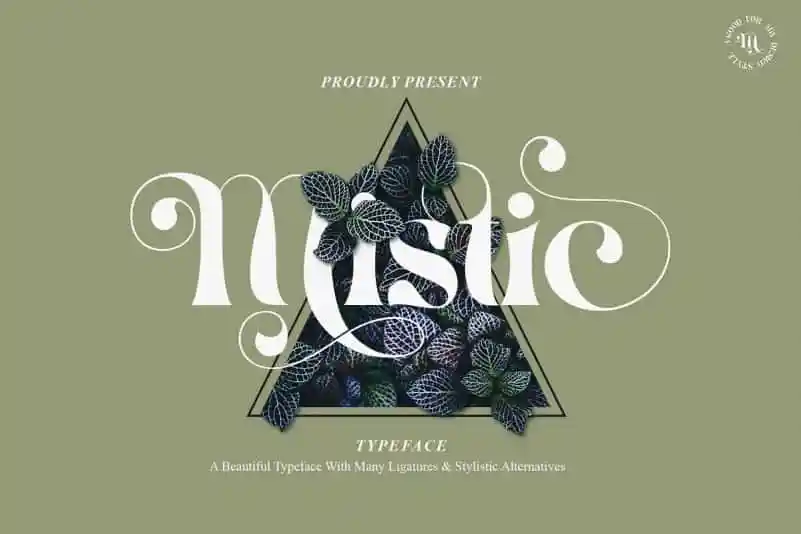
A Mistic Serif Font é uma escolha perfeita para quem busca um estilo elegante e sofisticado que destaca suas criações. Desenvolvida pelo alit design, esta fonte serif se destacou graças ao seu uso recorrente no setor dos casamentos. O conceito desta fonte é marcado por uma elegância brilhante, repleta de alternativas com letras curvadas, que adicionam um toque romântico às criações. Perfeita para trabalhos relacionados a temáticas como casamentos, cartões de aniversário, citações românticas e muitos outros temas relevantes. Englobando essas características, a Mistic Serif Font surge como uma opção irresistível para designers que procuram um toque único em seus projetos, seja na web ou impressa.